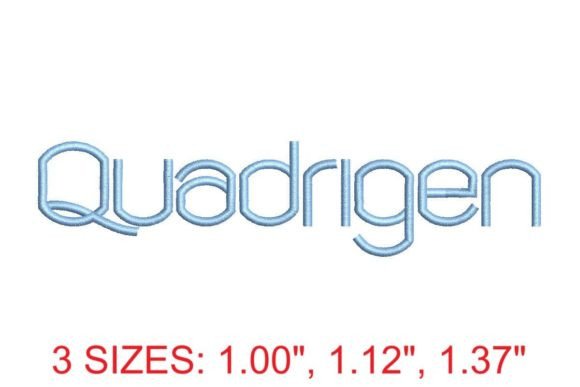
Quadrigen Embroidery Font
Việc tìm kiếm các thành phần thiết kế phù hợp có thể là một thách thức, nhưng Quadrigen Embroidery Font cung cấp một bộ sưu tập đặc biệt giúp nâng tầm công việc của bạn ngay lập tức.
Được chế tác với độ chính xác cao, Quadrigen Embroidery Font cung cấp các vector sạch, kiểu chữ mượt mà và giấy phép thương mại để bạn yên tâm.
Cho dù bạn đang tạo sản phẩm POD (In theo yêu cầu), thiệp mời đám cưới hay đồ họa mạng xã hội, Quadrigen Embroidery Font đều là một sự lựa chọn lý tưởng.